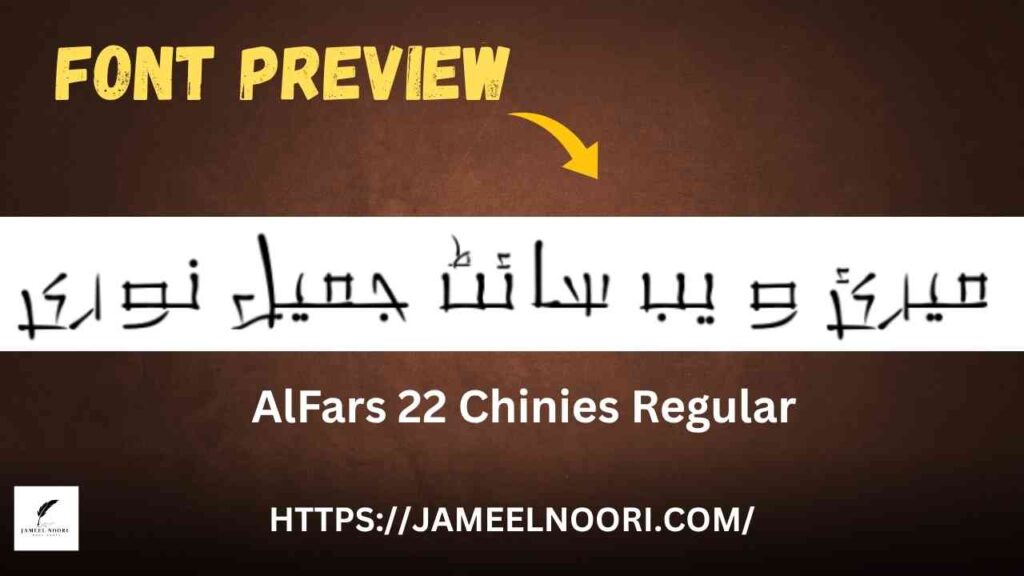
Introduction – Urdu Font AlFars Chinies Kya Hai?
AlFars Chinies Font Ke Features
• ✅ Stylish aur artistic Urdu typography
• ✅ Best for Urdu branding aur posters
Yeh Urdu Font Kahan Use Kiya Ja Sakta Hai?
AlFars Chinies Regular Font ko aap kai tarah ke Urdu-based kaamon mein use kar sakte hain:
• YouTube thumbnails & video titles
• ✅ Urdu poetry posters & calligraphy art
• ✅ Invitation cards aur graphic design
• ✅ Urdu social media content design
Conclusion – Apne Design Ko Stylish Banayein
Agar aap chahte hain ke aapka Urdu content stylish, modern aur eye-catching lage, to AlFars  Chinies Regular Urdu Font zaroor download karein.. Yeh font aapke graphic projects ko ek naya look dega, chahe woh social media ho ya print design.